Ulasan Fontcloud: Pengelola Font Online Gratis oleh Creative Fabrica
Apa itu Fontcloud?
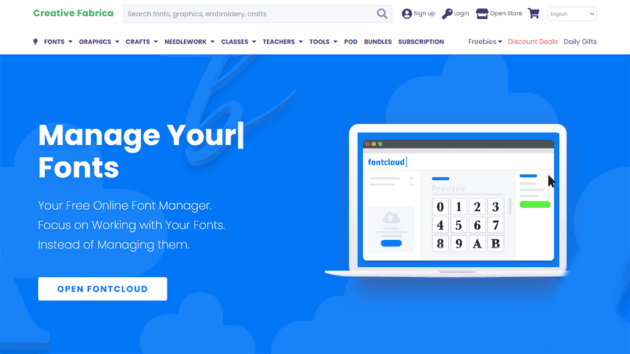
Fontcloud adalah alat pengelola font online oleh Creative Fabrica yang membantu Anda bekerja dengan font. Platform ini memungkinkan Anda mengelola alat font dari mana saja. Ini adalah alat yang sepenuhnya gratis untuk digunakan, dengan ribuan pekerja lepas dan seniman kreatif menggunakannya di seluruh dunia. Saat Anda membuat akun di Fontcloud, Anda akan mendapatkan sekitar 2 GB data tambahan yang membantu Anda menyimpan sekitar 10.000+ font.
Alat Fontcloud dapat digunakan di Windows, Mac, iPhone, iPad, Android, Aplikasi Photoshop & Ilustrasi, dan berbagai platform sosial, sistem operasi, dan perangkat lunak lainnya. Di bawah ini disebutkan beberapa fitur Fontcloud yang akan membantu Anda memahami platform dengan cara yang lebih baik. Atribut Fontcloud adalah sebagai berikut:
- Antarmuka pengguna dan kecepatan aplikasi ini sangat cepat, di mana Anda dapat mencari font eksklusif, menjelajahi, melihat, dan menambahkannya ke koleksi Anda dalam sekejap.
- Fontcloud memungkinkan Anda melihat semua font yang disimpan dalam ikhtisar sederhana. Sehingga Anda dapat menemukan yang tepat untuk proyek Anda hanya dengan satu klik.
- Platform ini juga memungkinkan Anda untuk melihat semua karakter dalam font dalam satu klik. Ini juga termasuk karakter yang disandikan PUA.
- Anda dapat menggunakan Fontcloud di mana saja dan di perangkat apa saja. Anda hanya perlu masuk ke akun Fontcloud Anda dan melihat font yang Anda simpan dan menggunakannya sesuai kebutuhan mereka.
- Fontcloud juga memiliki opsi untuk mengamankan cadangan Anda. Jika kebetulan Anda kehilangan font, platform ini membantu Anda, Anda dapat masuk ke Fontcloud dan mengunduh semuanya lagi dan bersenang-senang membuat proyek kreatif.
Gaya dan desain font yang berbeda
Untuk membuat proyek Anda menonjol dari yang lain, di keramaian, Anda perlu menggunakan font kreatif agar terlihat spektakuler. Oleh karena itu, atas bantuan Anda, Creative Fabrica telah meluncurkan Fontcloud, yang memiliki ribuan jenis font berbeda yang tersedia untuk digunakan secara gratis atau dengan tarif minimal. Ada sekitar 108.091 font yang dapat Anda unduh untuk digunakan dalam proyek web dan cetak. Font yang tersedia menampilkan karakter tambahan, hiasan, bentuk huruf vektor, kuas, gambar tangan, dll.
Di bawah ini adalah daftar beberapa gaya dan desain font yang tersedia di Fontcloud, periksa sebelum benar-benar mengunduhnya.
Font Skrip:
Jenis font ini elegan dan halus. Mereka bukan untuk menjadi lemah hati, karena mereka adalah yang terbaik dalam koleksi karena keserbagunaannya. Font biasanya merupakan jenis struktur tulisan tangan dengan hiasan yang membuatnya terlihat aneh dan sangat cantik. Beberapa font script populer yang patut dicoba adalah; Stylish, Hello October, Smile, Simply Bloom, Christmas Lights, Boho Mother, Handmade, Better Together, Simple House, dan sekitar 58.870 lainnya.
Font Tampilan:
Font Tampilan akan sangat berguna bagi Anda ketika Anda ingin memberikan pop tambahan pada proyek Anda agar terlihat menonjol. Ini adalah jenis huruf unik yang bisa digunakan untuk membuat poster, di berbagai proyek kerajinan dan posting blog. Mereka tampak hebat karena fokus utamanya adalah pada keterbacaan teks daripada berfokus pada keindahan estetika seperti font lainnya. Beberapa Font Tampilan yang populer dan paling sering digunakan adalah Chunky Retro, Good Vibes, De Augusta, Haunted Night, Spooky Season, Forever Dreaming, dan ribuan lainnya.
Kesimpulan
Fontcloud oleh Creative Fabrica adalah platform penghemat waktu yang sangat besar dengan fungsionalitas yang mudah digunakan dan ketersediaan yang mudah. Anda tidak perlu mengunduh Fontcloud dari sumber mana pun. Yang Anda butuhkan hanyalah browser untuk masuk ke halaman web platform. Jelajahi ribuan font mereka yang sangat indah secara online. Juga, tidak ada masalah dengan pembaruan dan masalah kompatibilitas dengan perangkat. Jika Anda juga seorang pecandu kreativitas, setelah Anda menyiapkan semuanya, Fontcloud akan menjadi bagian dari alur kerja reguler Anda dalam waktu singkat.